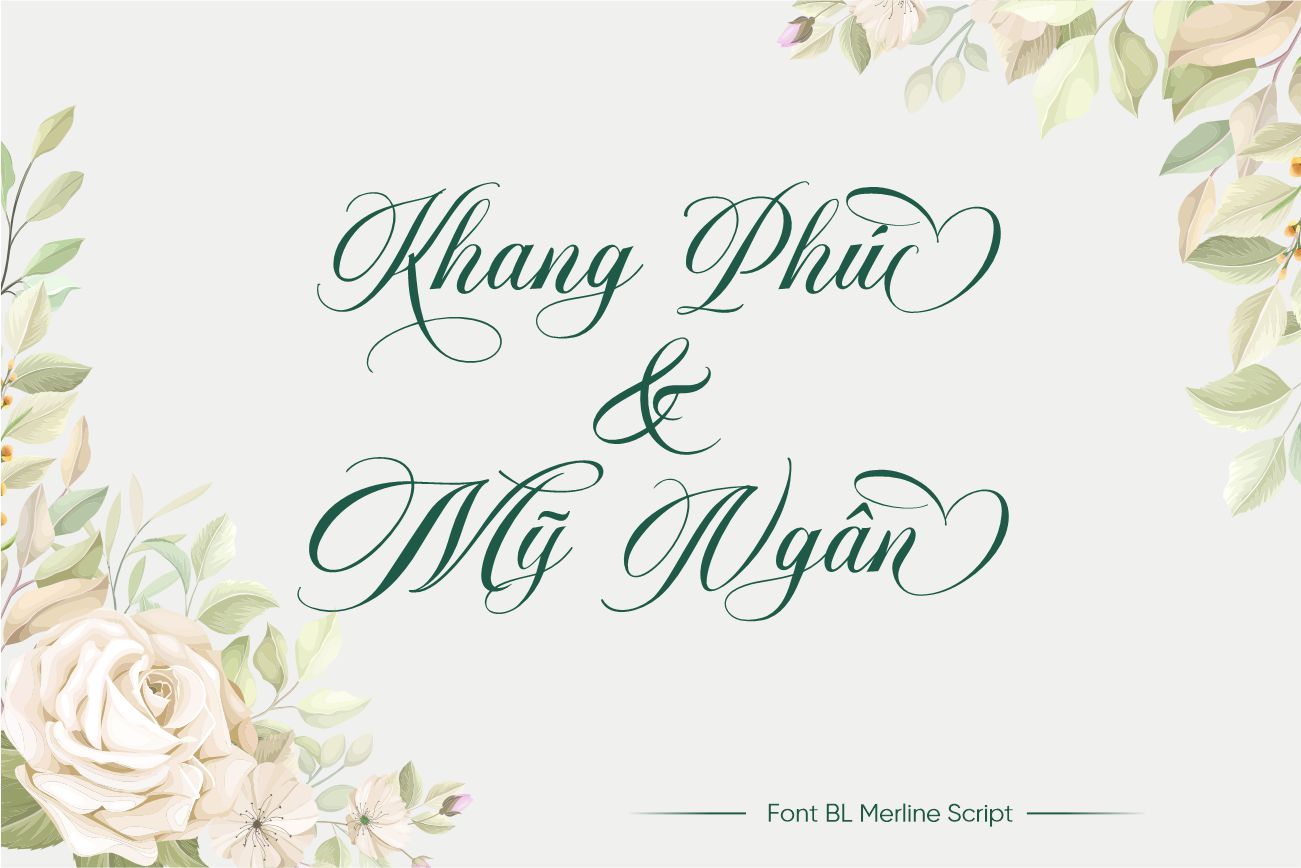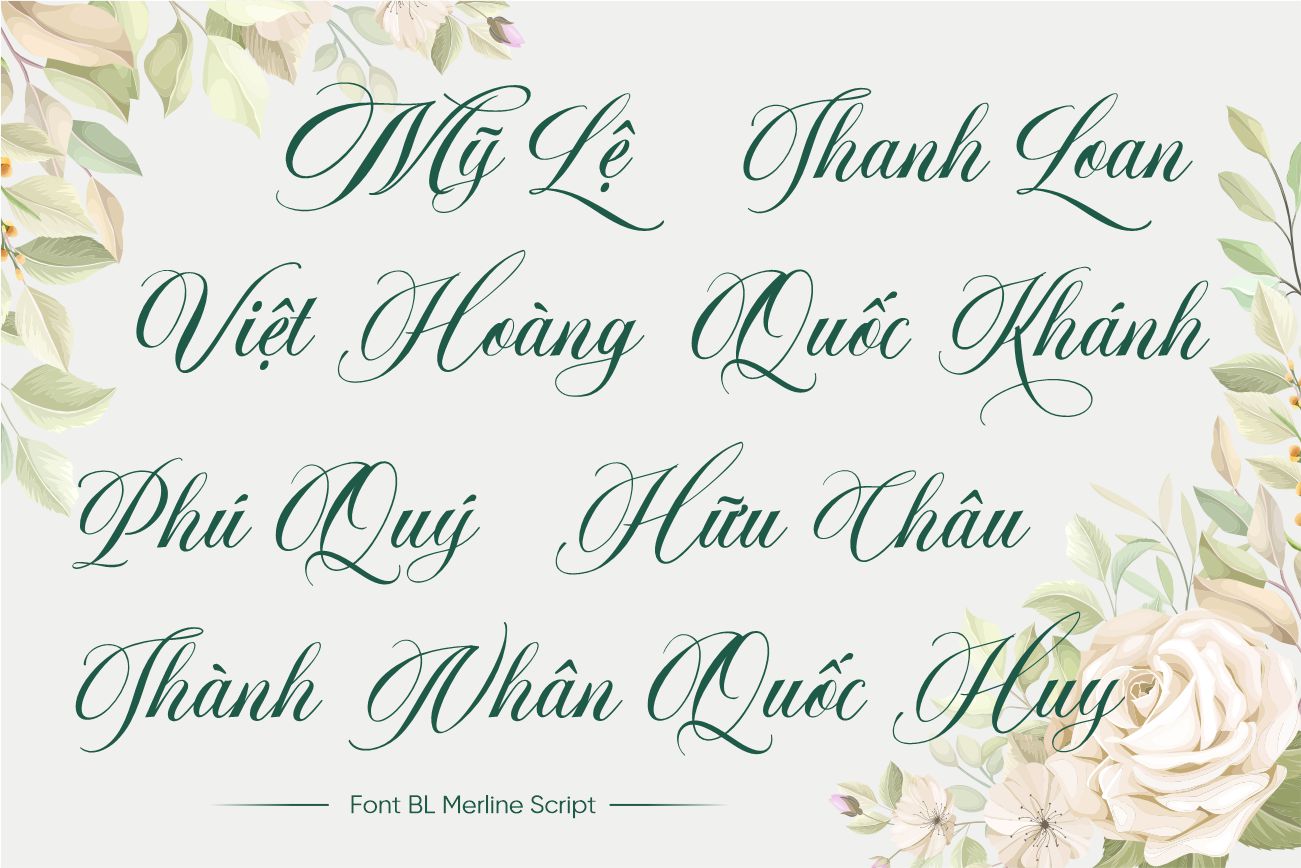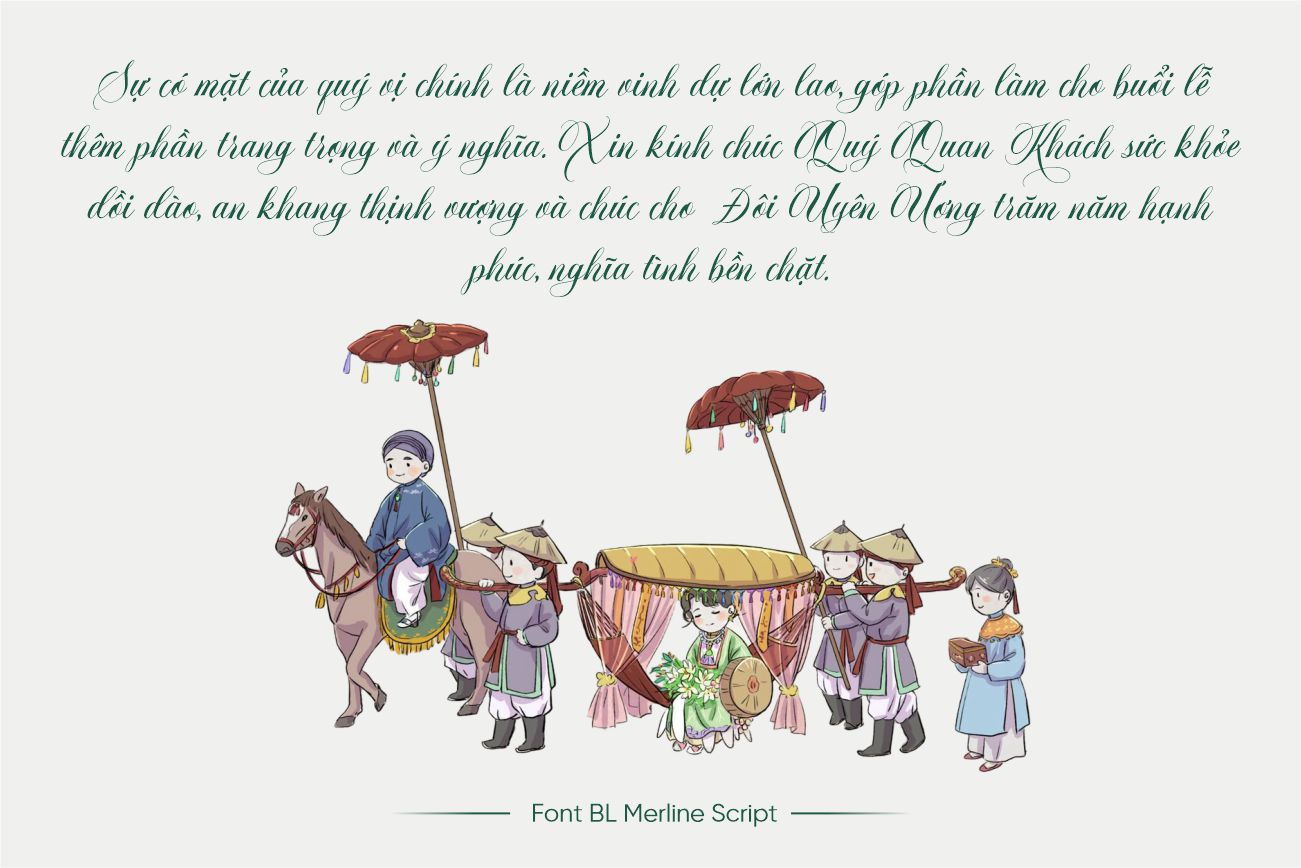
Font chữ Script nét mảnh BL Merline Việt hóa
Trong thế giới thiết kế đồ họa, font chữ script luôn được yêu thích bởi vẻ đẹp mềm mại, uyển chuyển và giàu cảm xúc. Đây là kiểu chữ mô phỏng nét viết tay tự nhiên, mang lại cảm giác gần gũi nhưng không kém phần sang trọng. Đặc biệt, khi kết hợp với font chữ nét mảnh, các tác phẩm thiết kế sẽ trở nên tinh tế, nhẹ nhàng và tạo ấn tượng thị giác sâu sắc.
Font chữ script nét mảnh thường được ứng dụng rộng rãi trong thiết kế thiệp cưới, lời mời sự kiện, logo thương hiệu cao cấp, poster thời trang hay các ấn phẩm truyền thông cần sự lãng mạn, bay bổng. Nét chữ mảnh mai giúp tổng thể thiết kế không bị rối mắt, đồng thời tôn lên sự thanh thoát, hiện đại.
Một ưu điểm lớn của các bộ font chữ script nét mảnh Việt hóa là khả năng hiển thị đầy đủ dấu tiếng Việt, đảm bảo tính thẩm mỹ và ứng dụng thực tiễn trong nhiều dự án. Các nhà thiết kế có thể dễ dàng tải về, sử dụng và kết hợp cùng những font chữ khác để tạo nên bộ nhận diện thương hiệu ấn tượng.